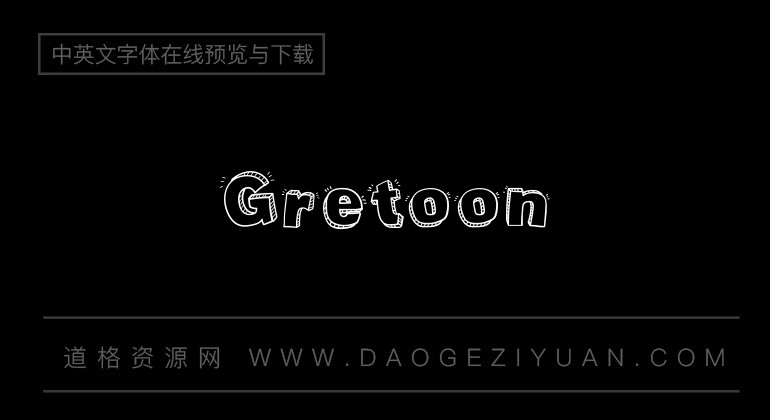
Gretoon 是一种设计独特的、适合用于漫画、卡通和插画的字体。该字体由设计师 Guillaume Seguin 在 2010 年创建,以传达一种轻松、有趣和幽默感的氛围。整个字体具有非常明显的手写风格,字母有一定的圆润和弯曲,同时还有一些小巧思,如斜体、下划线和弯曲符号。这些元素使得 Gretoon 字体非常适合用于一些有趣的或者童趣的设计中,如儿童书籍、漫画、卡通影片、海报等等。内容介绍
Gretoon是一款非常不错的手写艺术字体,具有很好的视觉感,适合于文化类的宣传设计、商业类品牌的广告和产品包装设计以及个性化文字排版等较多场景。